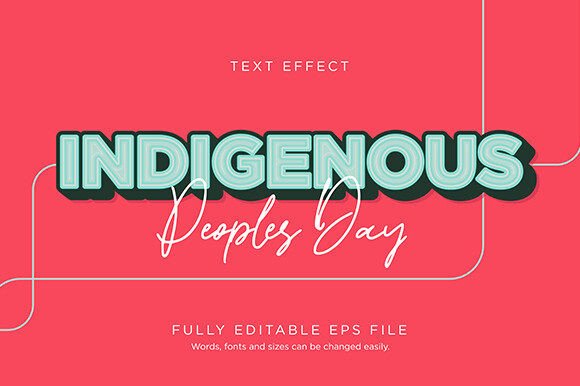
Indigenous Text Effect Font Type Vector
Jika anda sedang mencari aset berkualiti tinggi seperti Indigenous Text Effect Font Type Vector, pakej premium ini merupakan pilihan yang hebat untuk projek kreatif anda.
Dicipta dengan ketepatan, Indigenous Text Effect Font Type Vector menyediakan vektor yang bersih, tipografi yang licin dan lesen komersial untuk ketenangan fikiran.
Sama ada anda mencipta produk POD (Print on Demand), jemputan perkahwinan atau grafik media sosial, Indigenous Text Effect Font Type Vector amat bersesuaian.